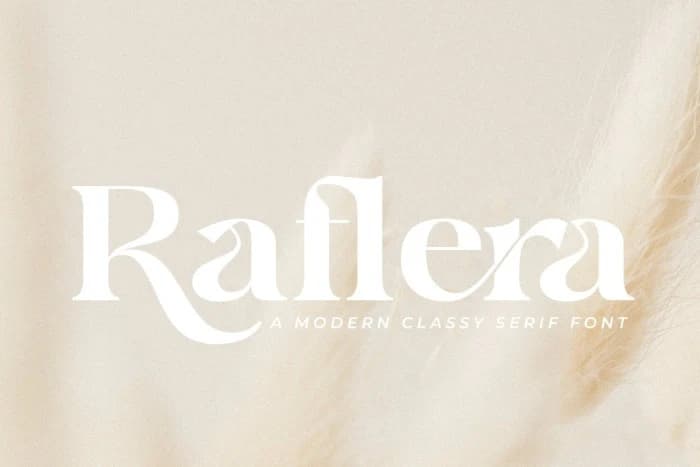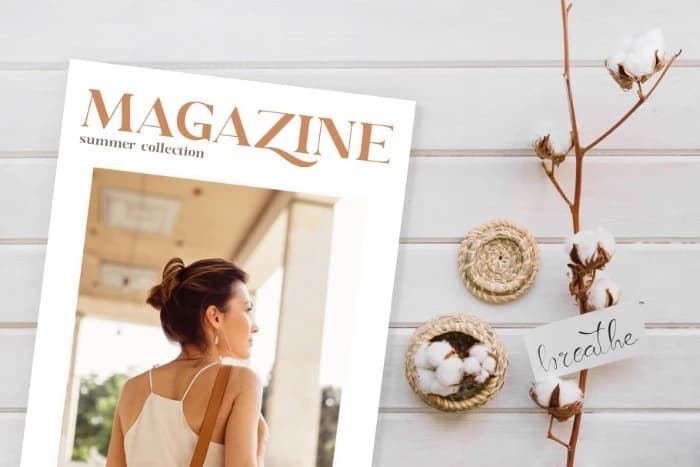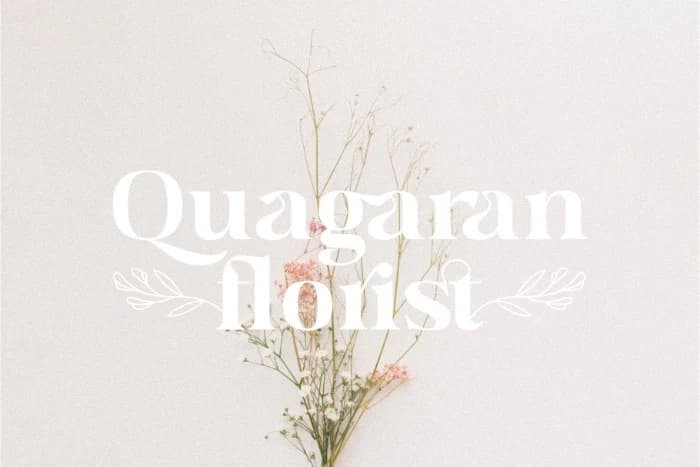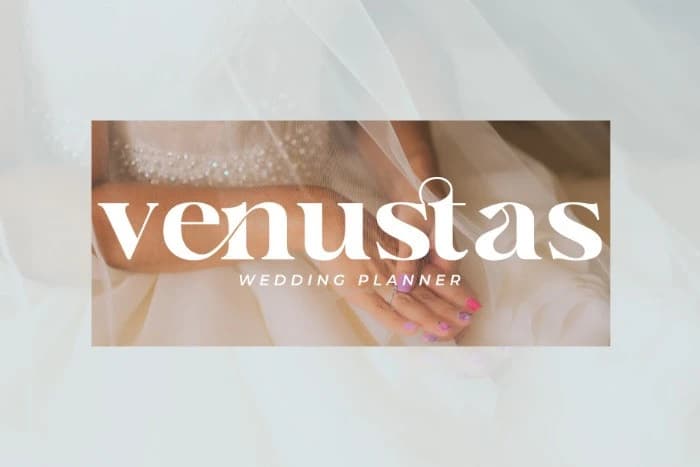
Raflera Font
Raflera Font, modern zarafeti zamansız bir şıklıkla zahmetsizce birleştiren bir yazı tipidir. Şık, yüksek kontrastlı glifleriyle çeşitli tasarım bağlamları için çok yönlü bir seçenek sunar; resmi davetiyelerden gündelik marka tasarımlarına kadar.
Raflera Font, modern zarafeti zamansız bir şıklıkla zahmetsizce birleştiren bir yazı tipidir. Şık, yüksek kontrastlı glifleri onu çeşitli tasarım bağlamları için çok yönlü bir tercih haline getirir; resmi davetiyelerden günlük markalaşmaya kadar.